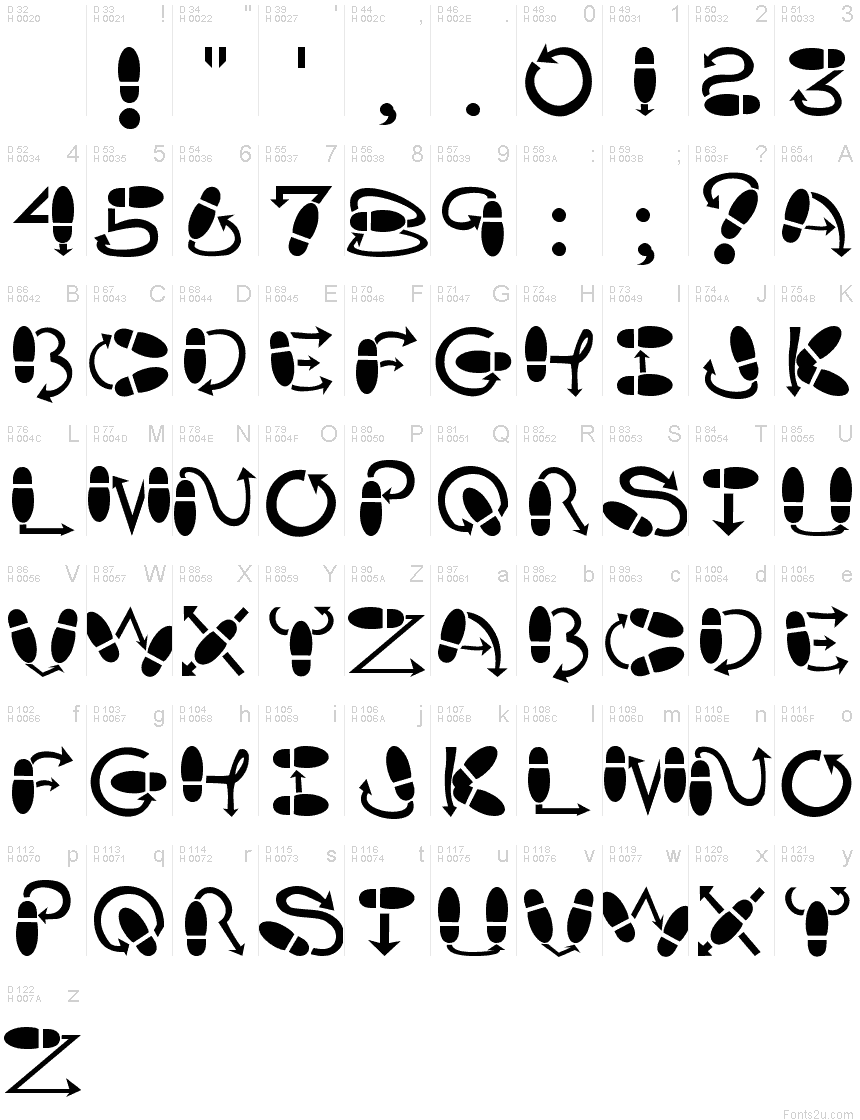
DanceStep di Fish Dicks è un font decorativo gratuito. Questo carattere giocoso sembra coreografato usando frecce e impronte. Le forme corpose e arrotondate sono vivaci e dinamiche, così che un titolo può quasi "muoversi" prima ancora di essere letto. È sfacciato, audace e pensato per catturare subito lo sguardo.
DanceStep è perfetta per volantini di scuole di danza, schede di coreografia, attività per bambini, poster di fitness, inviti, promozioni social, segnaletica ed emblemi grafici. Mantieni DanceStep grande per preservare la nitidezza dei dettagli e abbinala a un carattere sans serif pulito come Montserrat o Arial; questo font gratuito ama i partner sobri.